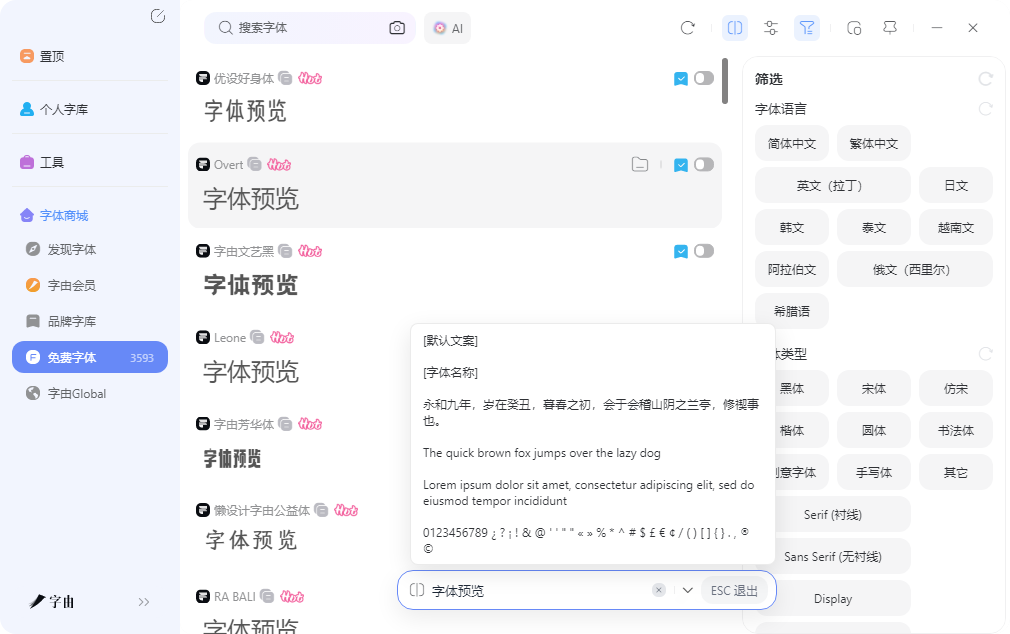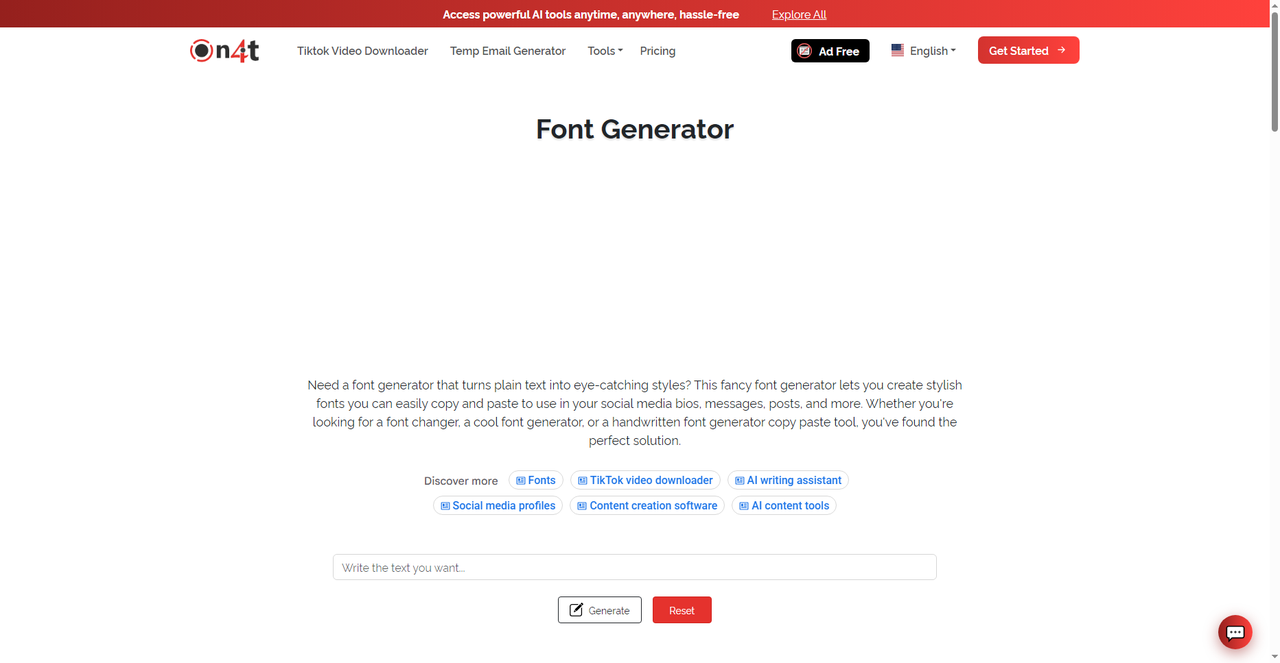
字体美化在线工具,Unicode花式字一键生成
发朋友圈或者写小红书笔记时,文案排版太单调容易让人一眼划过。系统自带的字体就那几种,想换风格只能加表情符号,效果有限。其实现在有不少在线工具专门解决这个问题,输入普通文字后一键转换成Unicode花式字体,花体、粗体、空心字、气泡字几十种样式随便挑,复制粘贴就能用,不需要下载任何软件。这篇文章整理的几个平台,有的样式数量多,有的支持实时预览,有的还能配合颜文字一起用,找合适的工具比较省心。
字由在字体美化这个方向上,提供的是真正的字体文件,而不是Unicode字符替换。客户端里的展示体和手写体分类,收录了不少本身就有装饰性的字体,笔画带粗细变化、有连笔特征、或者几何感强,直接用在标题里就比标准黑体更有设计感。对于需要做正式海报或者品牌物料的人来说,这种字体文件比网页转换的Unicode字符更可靠,跨平台显示不会乱码,印刷出来也更清晰。
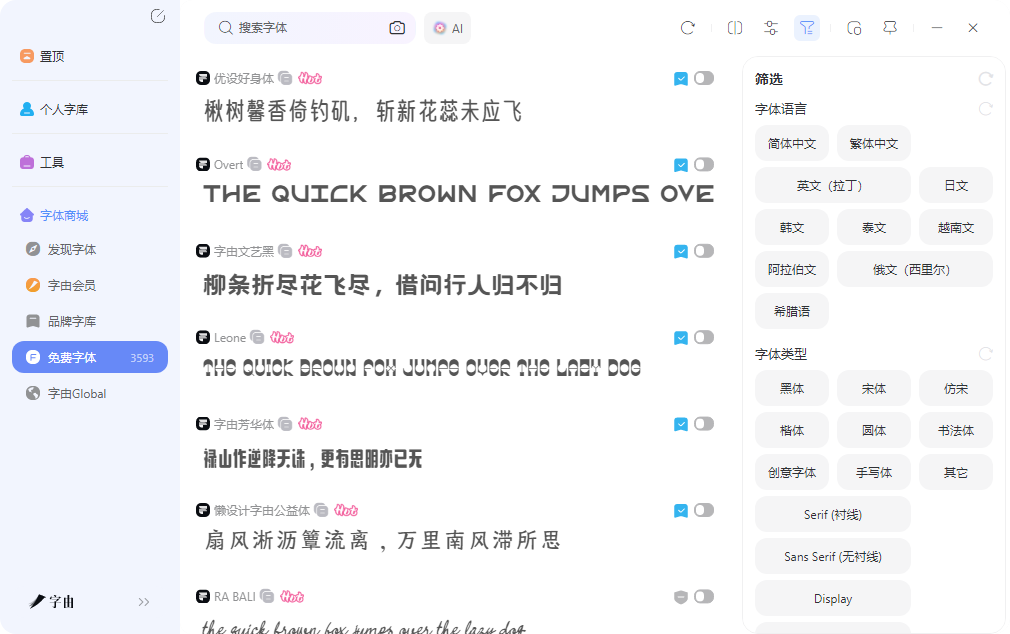
找装饰性字体时,字由的关键词搜索比较实用。输入"活泼""优雅""几何"这类描述词,系统会返回风格匹配的字体列表,比按分类逐个翻页效率高不少。每款字体都显示了字重数量,有些只有常规字重,有些支持从细到粗的全家族,做标题和正文混排时层次感很好。试排支持输入自己的文案,调整字号后观察笔画在不同大小下的清晰度,确认效果后再激活,避免了装完发现不合适再卸载的反复操作。
和网页Unicode转换工具相比,字由的优势在于字体可复用。网页工具生成的是特殊字符,改文案需要重新转换;字由激活的是字体文件,在设计软件里随时改文案、调字号、换颜色,灵活性高不少。对于需要做系列物料或者长期维护视觉风格的项目来说,字体文件比Unicode字符更实用。其中明确标注免费商用的会单独分类,做商业项目时直接筛选这个分类,授权问题比较清晰,不需要再去别的地方查授权状态。
2、ON4T
ON4T是一个综合性的字体美化平台,模板库覆盖了粗体、斜体、空心、气泡、双线、花体等几十种装饰样式。输入文字后选择样式类型,可以调整颜色、间距、背景透明度等参数,生成高分辨率的PNG图片。网站支持中文输入,部分样式对中文字符的渲染效果不错,笔画细节处理比较到位,做中文海报时不会出现笔画粘连。
3、Pretty Fonts
Pretty Fonts是一个专注女性化和优雅风格的字体美化平台,核心功能是把普通文字转换成带有装饰性的Unicode字符。输入文字后,系统提供花体、草书、细线体、双线体等偏优雅的样式,适合浪漫主题、生活方式、美妆护肤类的社交文案。每种样式都有独特的笔画处理方式,花体流畅自然,草书带有装饰性卷曲,细线体简洁现代,双线体复古精致。网站的操作界面比较简洁,文字输入框在上方,样式选择面板在下方。
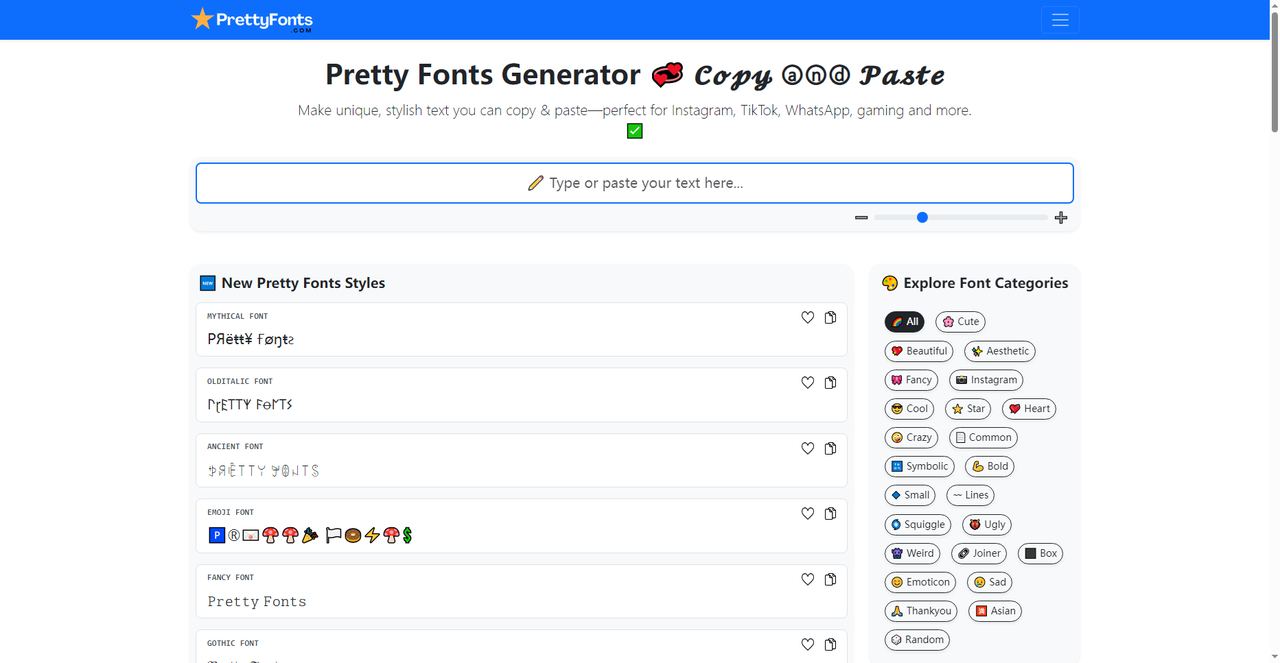
4、DesignWiz
DesignWiz的定位偏向设计辅助工具,除了Unicode花式字体转换,还提供了文字颜色渐变、背景阴影、边框描边等额外装饰效果。输入文字后选择字体样式,再调整颜色渐变方向和阴影深度,系统会实时生成预览图。这种组合式装饰比单纯换字体更丰富,适合需要稍微精致一点的社交文案。网站支持导出PNG图片,带透明背景,可以直接放进海报或者PPT里。
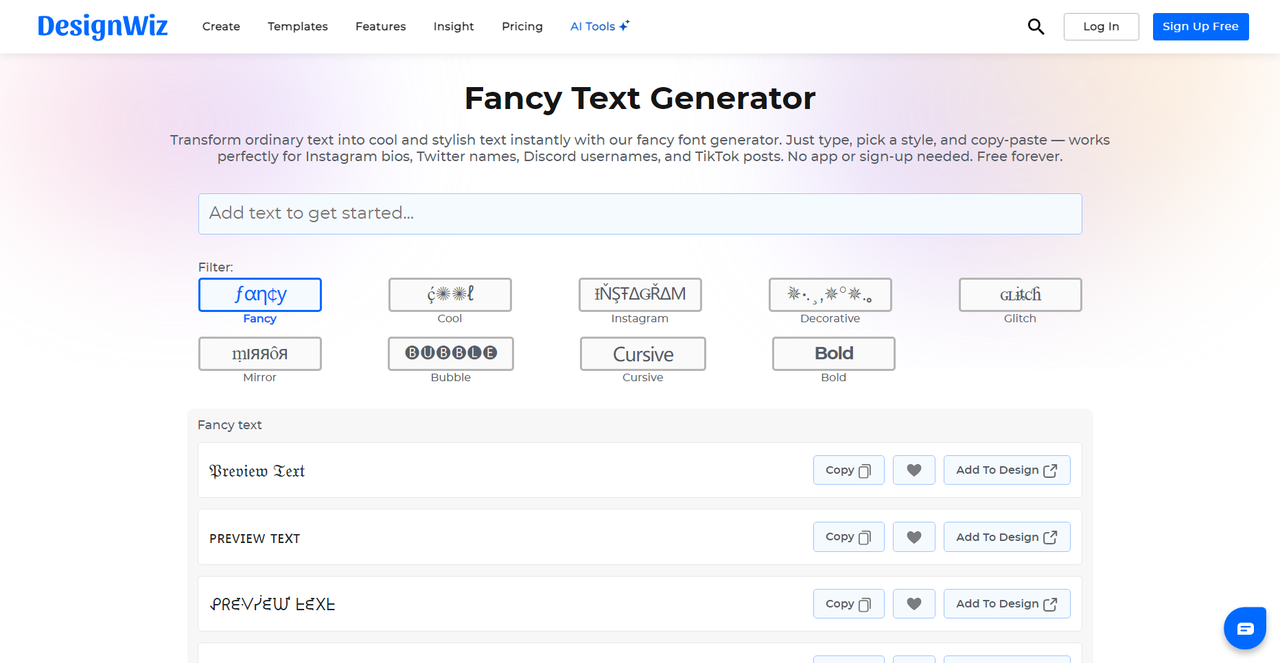
5、TextTrick
TextTrick是一个专注Unicode花式字体转换的在线工具,核心功能是把普通文字转换成几十种特殊字符样式。输入文字后,系统提供花体、粗体、斜体、空心字、双线字、气泡字等多种样式,一键复制就能粘贴到微博、小红书、抖音简介、朋友圈文案或者Discord频道里。这种转换走的是Unicode字符替换路线,不是生成图片,所以在任何支持Unicode的平台上都能正常显示,跨设备复制粘贴不会出现乱码。网站还整合了颜文字和特殊符号库,可以配合花式字体一起使用,让文案排版更有层次感。比如发一条产品推广文案,标题用粗体花字,正文用普通字体,中间插入几个特殊符号做分隔,整体阅读体验比纯文字好很多。
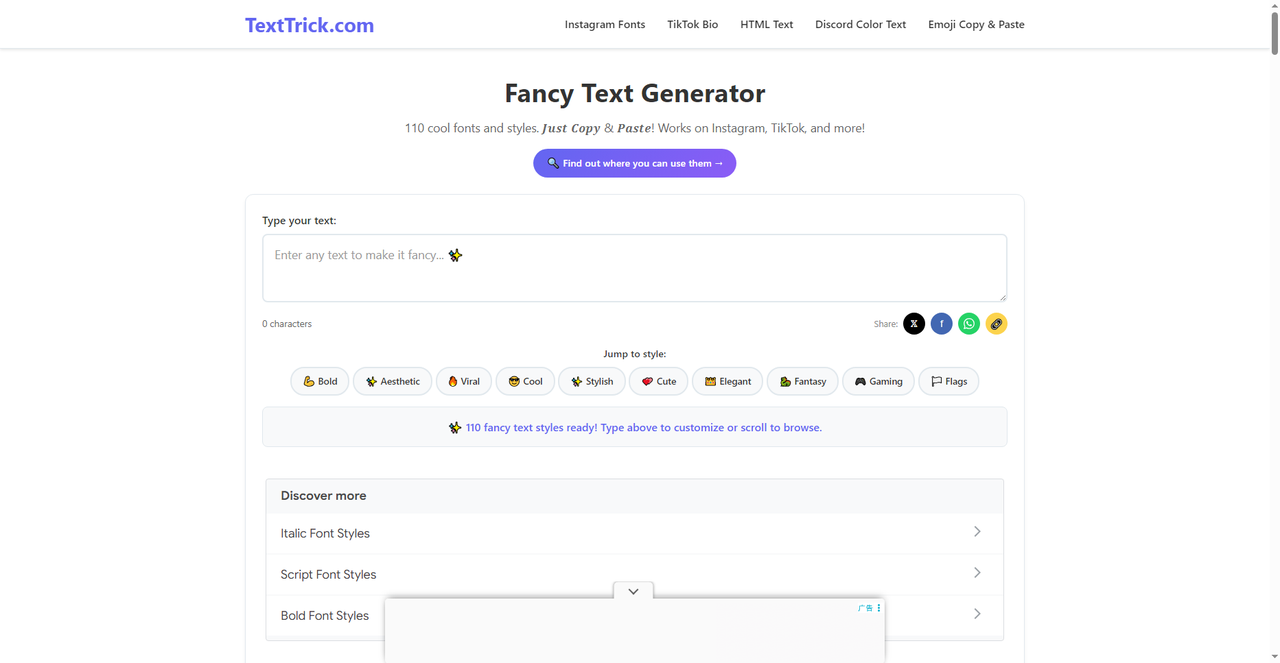
TextTrick的Unicode转换适合日常社交文案快速换风格,DesignWiz的渐变阴影适合稍微精致一点的装饰,Pretty Fonts的优雅样式适合生活方式类内容,ON4T的模板库覆盖面广,各种装饰样式都能找到。字由提供的是真正的字体文件,激活后在设计软件里随时调用,适合需要反复修改和长期使用的项目。网页工具胜在打开即用、复制粘贴就能用,字由胜在字体品质高、调用方便,可以按当下的任务类型灵活切换。